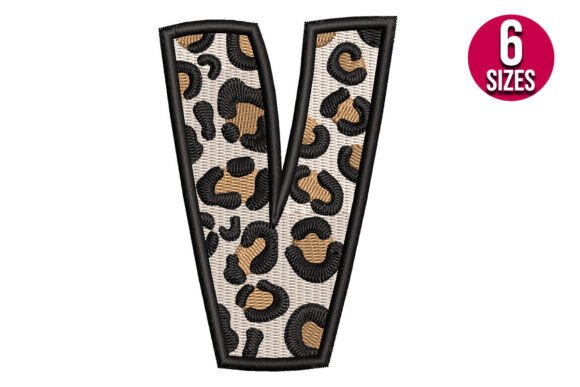
Leopard Print Alphabet Font Letter V
Leopard Print Alphabet Font Letter V – Review Completo
Se você está procurando um design de bordado que una ousadia e elegância, a letra V em estilo leopard print é a escolha perfeita. Ideal para monogramas modernos, peças de vestuário customizado ou acessórios fashion, este design se destaca em qualquer projeto criativo.
- Estampa leopard print vibrante – traz o toque selvagem e sofisticado que toda peça merece.
- Formato de letra Alphabet Font – garante legibilidade e estilo simultaneamente.
- Fácil de combinar – ótimo para criar monogramas duplos (ex.: “AV”, “MV”) ou para personalizar bolsas, camisetas e chapéus.
Por que escolher a letra V em leopard print?
Além da estética impactante, a letra V tem significado de vitória, estilo e versatilidade. Quando aplicada em couro sintético, denim ou algodão, o padrão de leopardo cria um contraste visual que atrai olhares e aumenta o valor percebido do produto final.
Ideal para:
- Criação de monogramas personalizados para marcas de moda.
- Peças únicas de custom apparel – camisetas, hoodies, jaquetas.
- Acabamento de acessórios – bolsas, carteiras, chapéus.
- Projetos de DIY para quem ama bordar e quer um toque premium.
O Leopard Print Alphabet Font Letter V é mais que um simples bordado; é uma declaração de estilo. Seja para criar um look exclusivo ou para oferecer um produto personalizado de alta qualidade, este design entrega resultados impressionantes e aumenta o apelo visual da sua marca. Não perca a oportunidade de transformar suas criações com esta letra icônica.